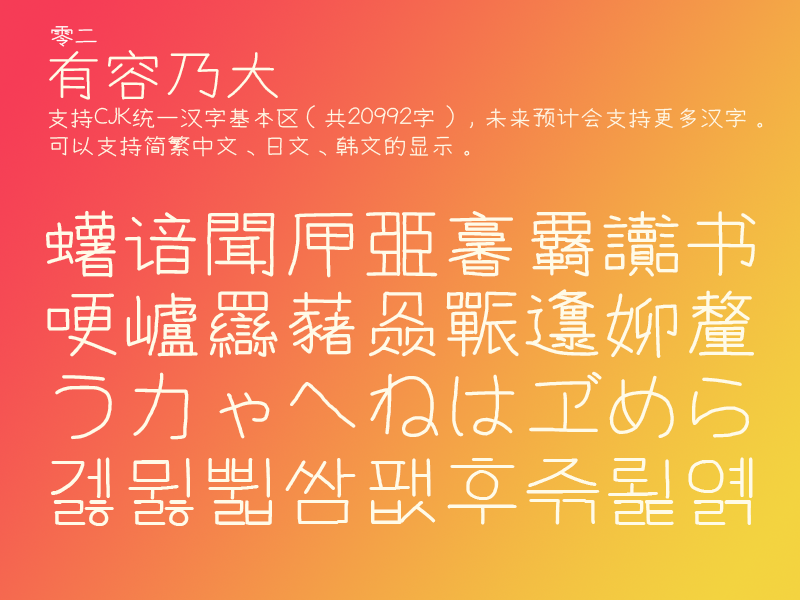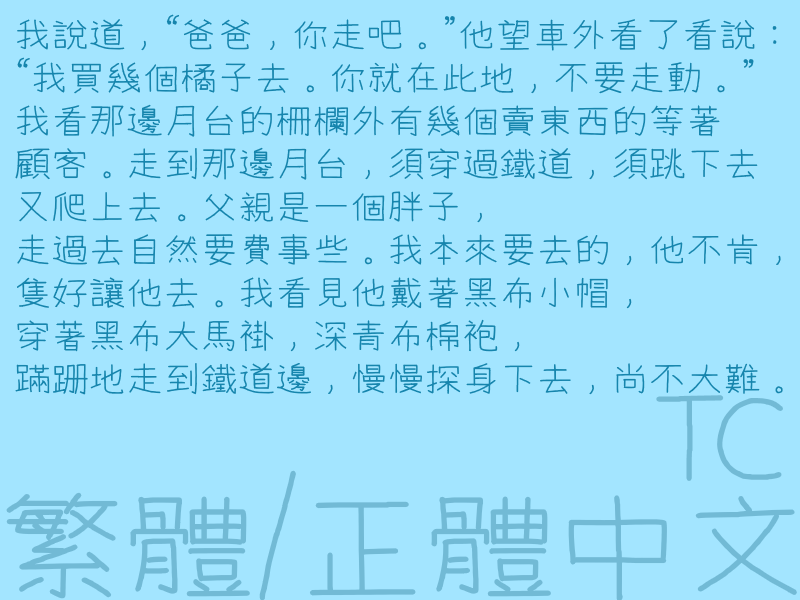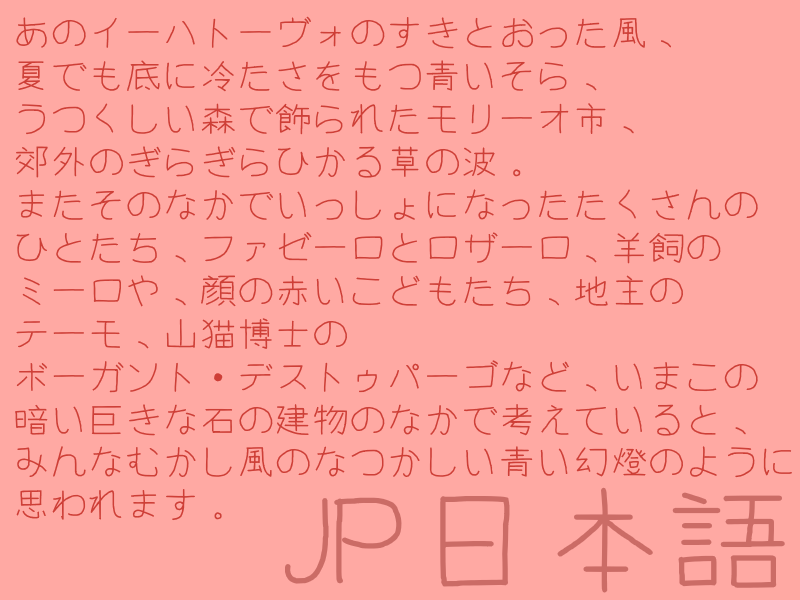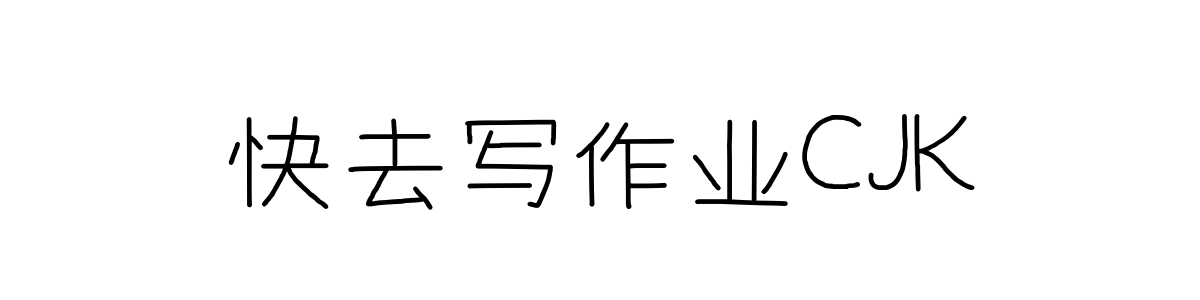
快去写作业CJK
快去写作业CJK(CEF Fonts CJK)是一款完全由鼠标绘制、覆盖海量字符,专为艺术创作设计的“仿”手写风格泛CJK字体。该字体由个人开发者从2020年4月25日起,历时两年多,纯粹使用鼠标(而非数位板)逐个点画完成。
其最核心的特征在于完全通过鼠标操作构建字形,轮廓上保留了明显的绘制痕迹。字体支持中日韩越统一表意文字基本区(20,992字) 与扩展A区(6,592字) 的绝大部分汉字,并包含部分扩展B区及以外的字符,总计超过27,000字,为简体中文、繁体中文、日语及韩语提供了基础的显示支持,字库规模庞大。
字形标准以中国大陆国标字形为主,混杂少量港台、日本及其他非标准字形。字体还包含可无限延长的破折号(非等宽版)、变体假名、化学元素汉字等特色功能。需要注意的是,它不支持变体序列,部分日语文本显示可能出错,且不适用于汉喃文。
字体风格
快去写作业CJK 脱离了传统书法或专业字体的美学框架,也不同于自然手写体的流畅感。其每一个笔画都清晰可见鼠标点击、拖拽形成的生硬转折、不稳定的曲线和微妙的锯齿感,这种“数字笨拙”构成了其最独特的视觉标识。
它模仿的是手写的随意性,但实现方式却是极度机械和耗时的鼠标操作,这种矛盾赋予了字体一种当代的、近乎行为艺术般的创作质感。整体字形偏向学生笔记般的放松结构,笔划粗细不均,带有一种未加修饰的质朴感和强烈的个人创作印记。